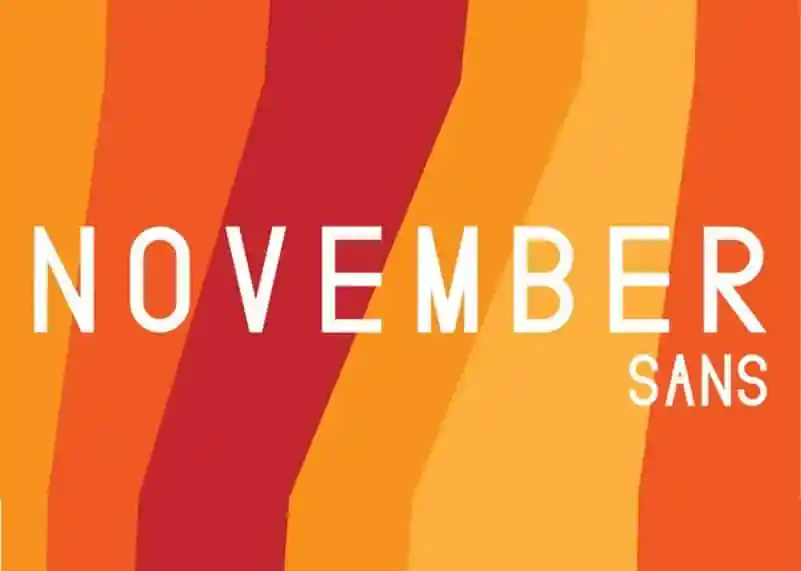
November Sans Serif é uma elegante fonte de tipo sans serif projetada para áreas visuais modernas. Seu design fresco e limpo remete a uma tarde morna de novembro, proporcionando um toque de tranquilidade ao seu trabalho gráfico. Este tipo de letra perfeito para headlines, banners, painéis e outros materiais publicitários. É uma fonte gratuita que combina facilmente com vários ambientes, oferecendo aos designers e profissionais da mídia uma opção versátil e moderna. Mackenzie Davenport é o designer responsável por este projeto criativo e inspirador.